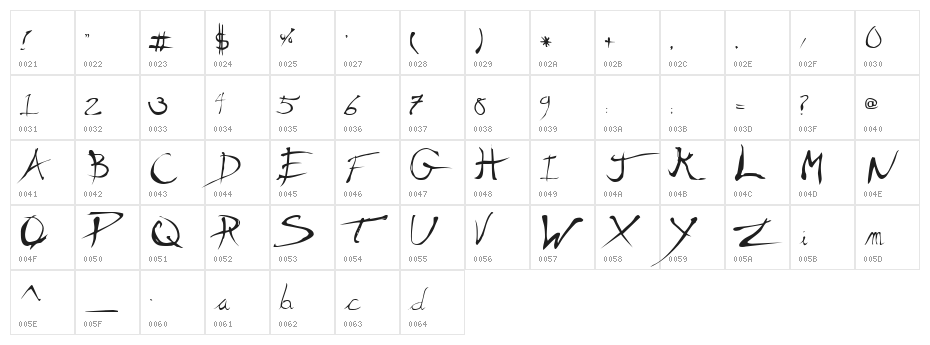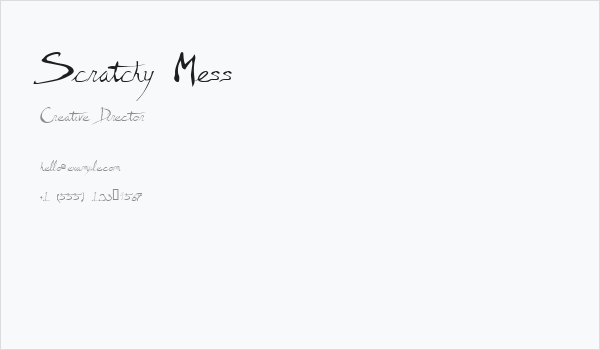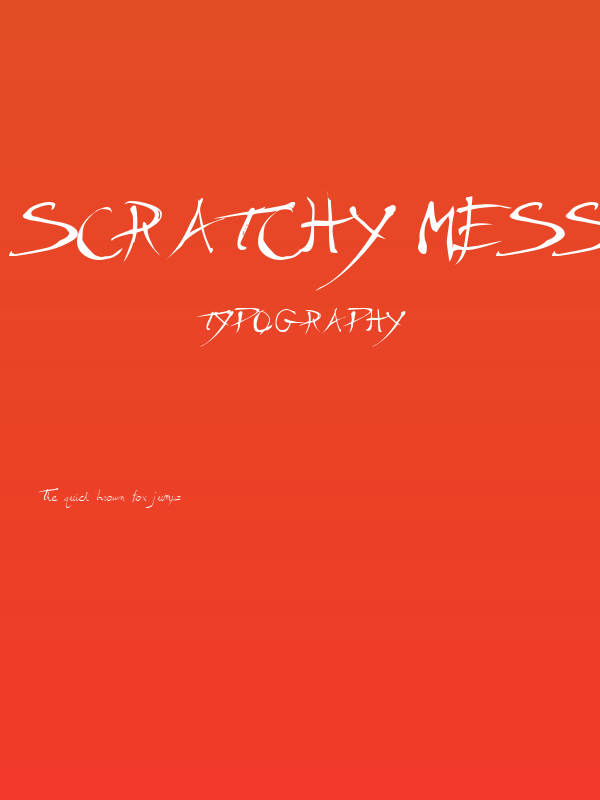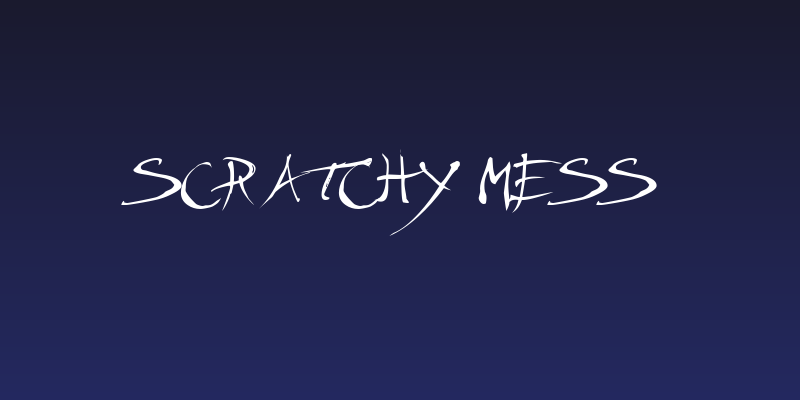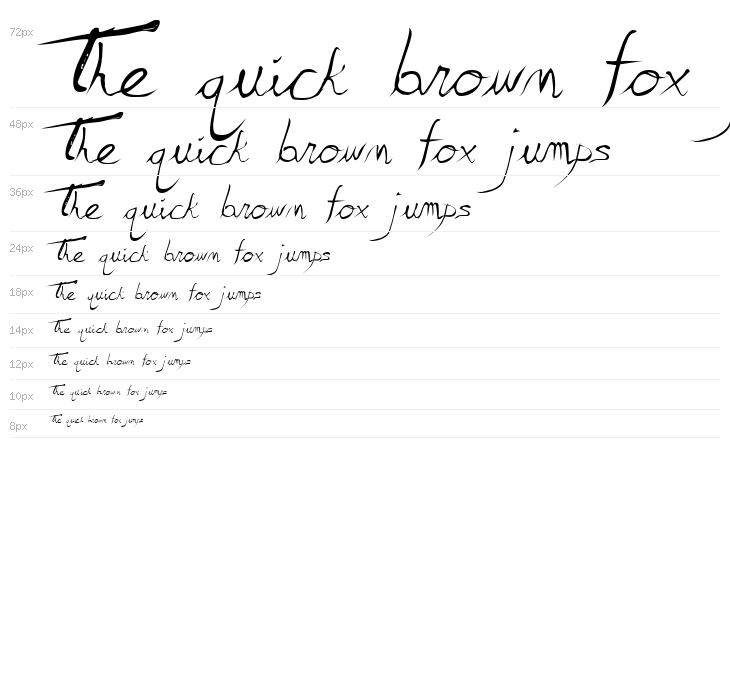
Scratchy Mess Font
| श्रेणियाँ | Kids |
| कंट्रास्ट | High |
| समग्र शैली | Decorative |
| उपयोग का मामला | Logos, Headlines, Artistic projects |
| सुझाए गए प्रोजेक्ट | Ideal for album covers, graffiti art, edgy branding, and creative posters. |